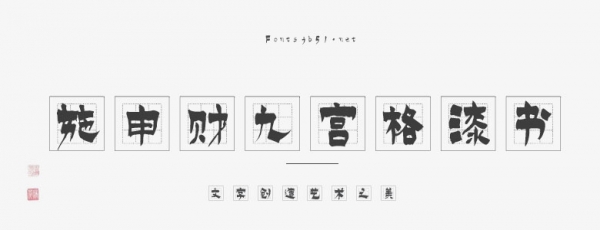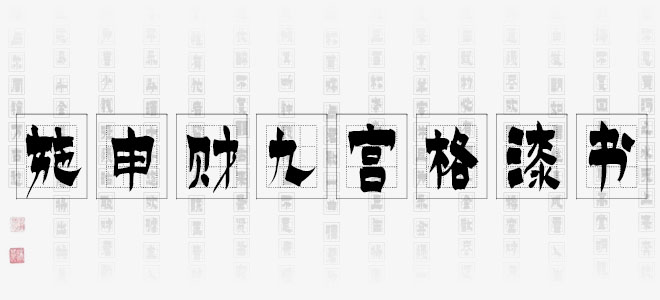
施申財(cái)九宮格漆書是一款自帶九宮格背景效果的書法藝術(shù)字體,具有強(qiáng)烈的視覺沖擊力。適用于海報(bào)、電商海報(bào)設(shè)計(jì)、店鋪設(shè)計(jì)、標(biāo)志設(shè)計(jì)、字體設(shè)計(jì)等領(lǐng)域。
施申財(cái)九宮格漆書